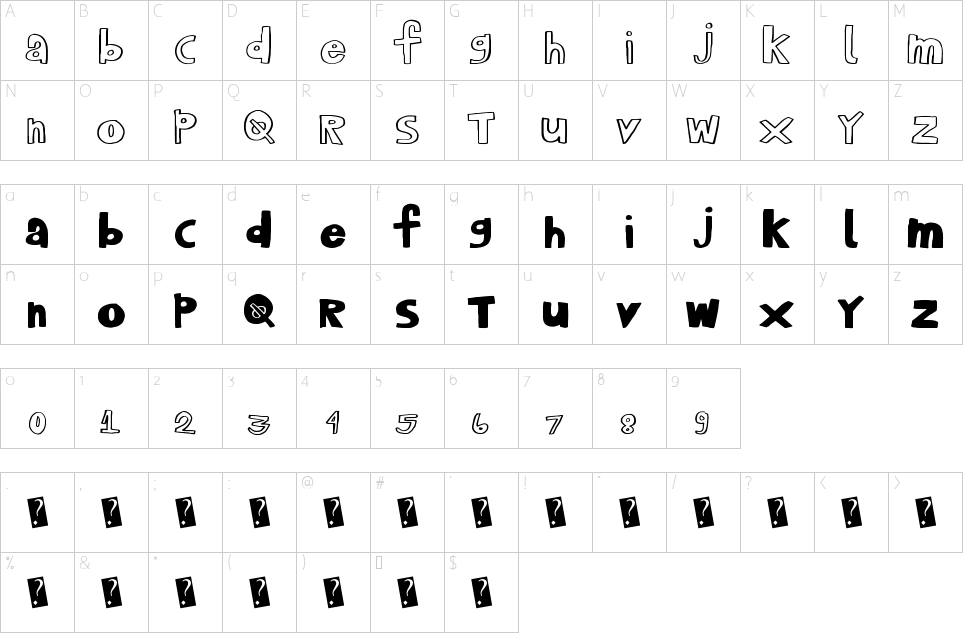
A Playhouse é uma fonte de graça para Windows e Mac, projetada pelo Xerographer Fonts. Esta fonte é perfeita para aqueles que procuram uma solução elegante e versátil para textos em suas produções digitais. Com seus traços suaves e uma paleta de cores que vai desde o básico até o delicado, a Playhouse se adequa perfeitamente a aplicativos de design gráfico e publicidade. O fato de ser uma fonte gratuita não diminui a qualidade ou a funcionalidade desta fonte. Ela é um ótimo exemplo de como você pode manter um nível alto de design e estilo ao mesmo tempo em que economiza tempo e dinheiro. Com 2,119 downloads, a Playhouse já foi utilizada por muitos designers que valorizam a praticidade e a qualidade combinadas. Navegue para a Playhouse Font para Windows e Mac e descubra por si mesmo por que esta fonte se tornou um favorito entre os designers digitais.